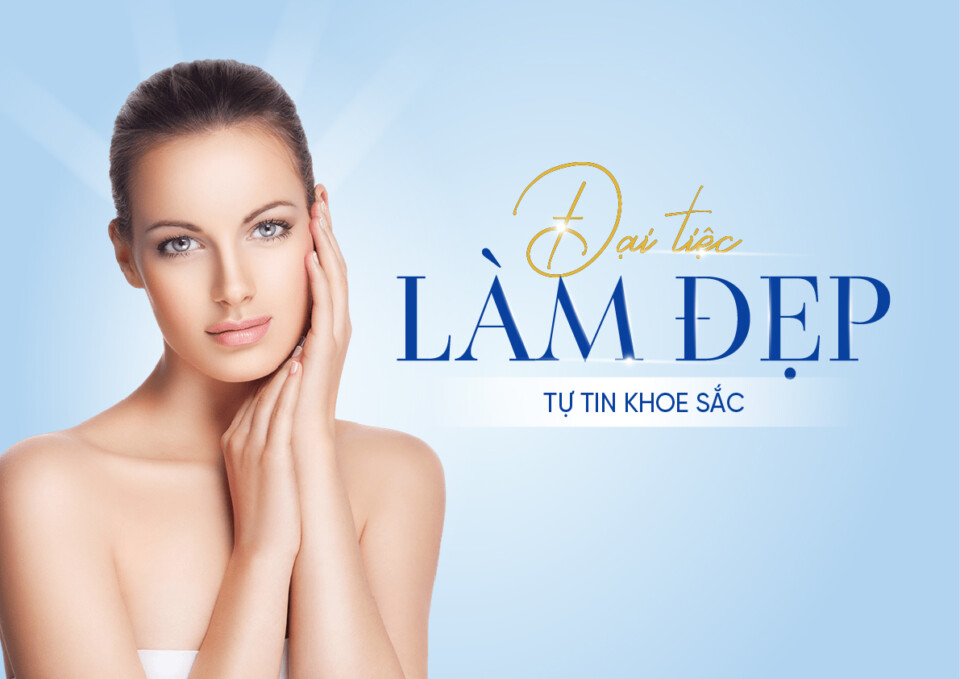
Combo font chữ Spa 2 kèm hiệu ứng chuyên nghiệp cho thiết kế làm đẹpTầm quan trọng của Combo font chữ Spa 2 kèm hiệu ứng trong ngành thẩm mỹTrong lĩnh vực kinh doanh dịch vụ làm đẹp và chăm sóc sức khỏe, việc xây dựng một bộ nhận diện thương hiệu ấn tượng là yếu tố sống còn để thu hút khách hàng tiềm năng. Việc sử dụng Combo font chữ Spa 2 kèm hiệu ứng không chỉ đơn thuần là chọn lựa các kiểu chữ đẹp mắt mà còn là cách để truyền tải thông điệp về sự tận tâm, tinh tế và sang trọng. Đối với những nhà thiết kế chuyên nghiệp hay các chủ tiệm spa đang tìm kiếm giải pháp đồ họa tối ưu, bộ sưu tập này cung cấp đầy đủ các công cụ cần thiết để tạo nên những ấn phẩm truyền thông độc đáo. Khi kết hợp cùng Font Miễn Phí, người dùng có thể dễ dàng tiếp cận với những xu hướng thiết kế mới nhất mà không tốn kém quá nhiều chi phí bản quyền. Sự mềm mại của các nét chữ viết tay kết hợp với hiệu ứng đổ bóng hoặc ánh sáng vàng đồng sẽ làm nổi bật lên giá trị cốt lõi của thương hiệu, giúp khách hàng cảm nhận được sự thư thái ngay từ cái nhìn đầu tiên vào bảng hiệu hay menu dịch vụ.Các đặc điểm nổi bật của bộ sưu tập font chữ dành cho SpaSự kết hợp hoàn hảo giữa nét cổ điển và hiện đạiBộ Combo font chữ Spa 2 kèm hiệu ứng được tuyển chọn kỹ lưỡng để đảm bảo tính ứng dụng cao trong nhiều hoàn cảnh khác nhau. Các font chữ Serif có chân mang lại cảm giác tin cậy, vững chãi cho các tiêu đề chính, trong khi các font Script bay bổng lại tạo nên điểm nhấn quyến rũ cho các chương trình khuyến mãi hay lời chào mời. Điểm đặc biệt của combo này chính là các tệp hiệu ứng đi kèm như lớp phủ kim loại, hiệu ứng chữ nổi 3D hoặc các mẫu gradient màu pastel nhẹ nhàng. Điều này giúp người thiết kế tiết kiệm thời gian chỉnh sửa thủ công mà vẫn đạt được kết quả thẩm mỹ tối đa. Các ký tự đều được tối ưu hóa hiển thị sắc nét trên cả màn hình điện thoại lẫn các bản in khổ lớn, giúp thông điệp của bạn luôn đồng nhất và chuyên nghiệp trên mọi nền tảng kỹ thuật số.Tương thích cao với các phần mềm thiết kế phổ biếnKhông chỉ dừng lại ở vẻ đẹp bên ngoài, bộ font này còn được định dạng linh hoạt để tương thích tốt với Adobe Photoshop, Illustrator và Canva. Người dùng có thể dễ dàng thay đổi kích thước, màu sắc hoặc tùy chỉnh các hiệu ứng đi kèm theo phong cách riêng của thương hiệu. Đối với những người mới bắt đầu học thiết kế, việc sở hữu một bộ công cụ có sẵn hiệu ứng giúp họ nhanh chóng làm quen với quy trình sáng tạo và tạo ra những sản phẩm chất lượng cao như dân chuyên nghiệp. Mỗi ký tự trong bộ font đều được kiểm tra kỹ lưỡng để tránh lỗi hiển thị, đảm bảo quá trình thiết kế diễn ra trơn tru nhất.Cách ứng dụng hiệu quả Combo font chữ Spa 2 kèm hiệu ứng vào thực tếĐể tận dụng tối đa sức mạnh của Combo font chữ Spa 2 kèm hiệu ứng, bạn nên phân chia vai trò của từng kiểu chữ trong thiết kế. Ví dụ, tiêu đề của poster nên dùng các font chữ đậm, có hiệu ứng ánh kim để tạo sự chú ý mạnh mẽ. Ngược lại, phần nội dung mô tả chi tiết dịch vụ nên sử dụng các font chữ không chân đơn giản để đảm bảo khách hàng dễ đọc và dễ hiểu. Đừng quên kết hợp các khoảng trắng hợp lý để tạo cảm giác thoáng đãng và thanh lịch cho bản thiết kế. Việc sử dụng màu sắc chủ đạo đồng nhất với logo của spa cũng là một mẹo nhỏ giúp tăng tính nhận diện thương hiệu. Khi bạn hoàn thành dự án, một bộ font chuẩn chỉnh sẽ là chìa khóa giúp doanh nghiệp nâng tầm đẳng cấp trong mắt khách hàng.Kết luận về giải pháp thiết kế tối ưu cho thương hiệu làm đẹpSở hữu một bộ công cụ đồ họa mạnh mẽ như bộ sưu tập này sẽ giúp bạn tự tin hơn trong việc xây dựng hình ảnh thương hiệu. Hãy truy cập ngay vào Font Miễn Phí, Font Việt Hóa, Combo font chữ Spa 2 kèm hiệu ứng để tải về và trải nghiệm những tính năng tuyệt vời mà bộ font này mang lại. Đây chắc chắn là sự đầu tư xứng đáng cho bất kỳ ai muốn tạo ra những tác phẩm nghệ thuật đỉnh cao trong ngành làm đẹp.
Combo font chữ Spa 2 kèm hiệu ứng